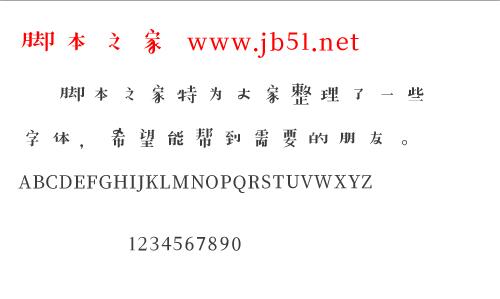
站酷创意宋是一款别具一格的宋体字,在保留宋体字基本特质的前提下,对多处细节进行了创意变形与设计:撇捺、提勾等笔画之间的连笔设计,俏皮而灵动,增添了字体的亲近感;不同结构的字面变化,带来了鲜明的节奏感,活泼有趣,错落有致。。。。正是这样的风格创新,让这款字体在设计应用上拥有了更多的可能性,在品牌形象,海报招贴,产品包装等方面,这款字体,都会带来优质而独特的展示效果。
这款字体设计由刘兵克工作室创作完成,历时一年左右。
字库字数:简繁+符号,9283字